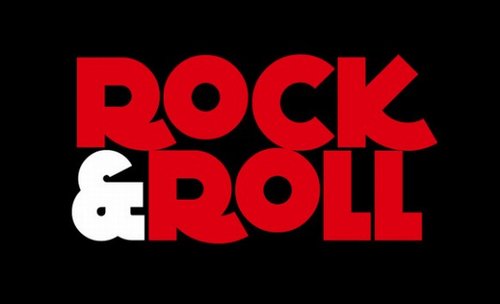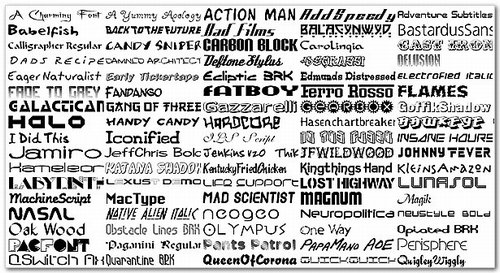
In tipografia e in informatica il tipo di carattere o font è un insieme di caratteri tipografici caratterizzati da un certo stile grafico.
La scelta di un font per questo motivo, è di fondamentale importanza per la riuscita di un progetto, perché a seconda del tipo di lavoro che dobbiamo sviluppare occorrerà usare un tipo di carattere piuttosto che un’altro.
Le famiglie di font si suddividono generalmente in graziati, bastoni (senza grazie) e decorativi, ma i progettisti devono tenere conto nel corso delle proprie elaborazioni di altri fattori come l’apertura (l’andamento delle aste curve aperte), dimensioni, proporzionalità e crenatura ossia la riduzione dello spazio in eccesso tra le due lettere.
Dopo questa piccola spiegazione, vi proponiamo alcuni font totalmente gratuiti che gli addetti ai lavori potranno usare portando un valore aggiunto ai propri lavori.